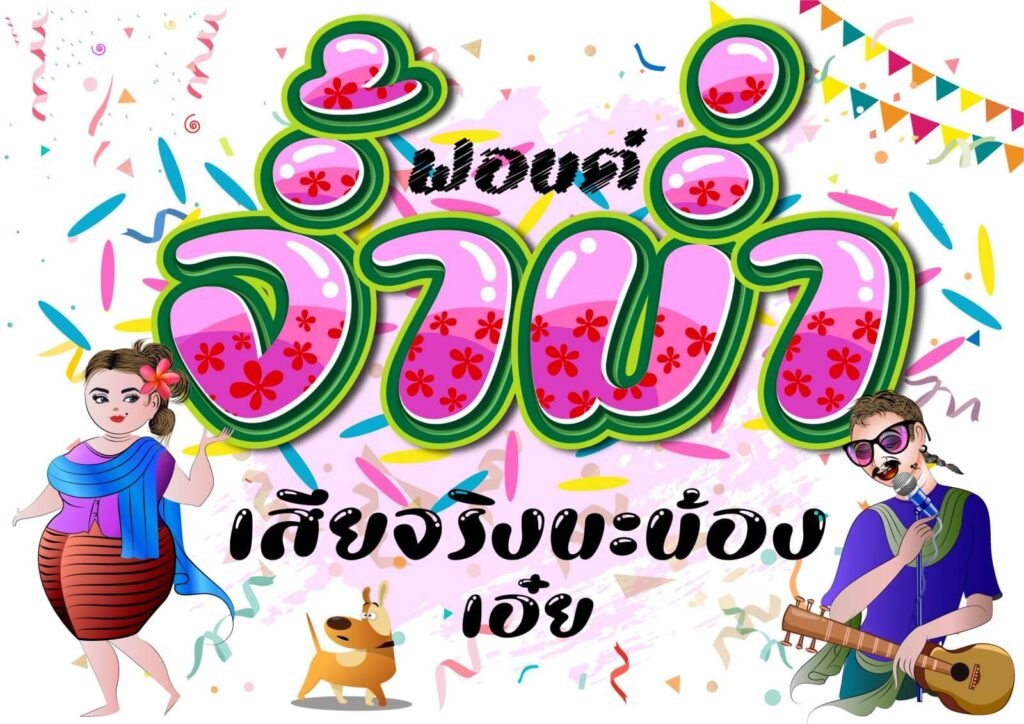
จ้ำม่ำ หน้ารวมมิตร (SP_Chammam)4
เป็นรูปแบบอักษรไม่มีหัว แนวแฟนตาซี คอมิดีการ์ตูน น่าร้าก…น่าชัง น้อนมีชื่อว่า “จ้ำม่ำ” มีทั้งแบบปกติ แบบตัวทับซ้อน พร้อมลวดลายกราฟิก โรยหน้าด้วยข้าวงอกบุบผกามาลาธัญพืช-ท็อปปิงเรนโบว์ แต่งสี 5 โทน 11 ชั้นเทมเพลต ฟรุ้งฟริ้ง-มุ้งมิ้งน่ากิ๊น…น่ากิน
แถมเอฟเฟกต์ฟีเจอร์ให้เสร็จสรรพ พร้อมใช้งานแสดงผลแบบอัตโนมัติทันที
ครอบคลุมการใช้งานทุกแพลตฟอร์ม ใช้ฟีเจอร์ แยกนิคหิต-สระอำ-วรรณยุกต์ รองรับการพิมพ์ภาษาบาลีแบบโบราณอีกตะหากแน่ะ